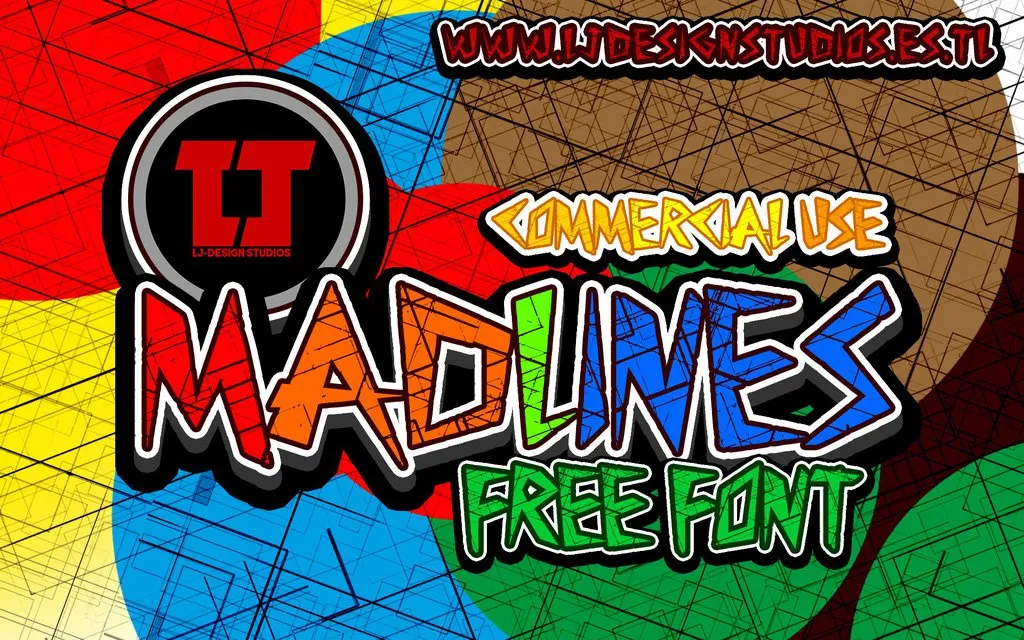
MadLines é uma fonte de graffiti criada pelo designer Hamilton. Ideal para quem busca estilo vibrante e ousado no seu design, esta fonte traz a essência do grafite urbano com liberdade e personalidade. Suas formas livres e coloridas são perfeitas para criações que desejam expressar-se de maneira única e autêntica. Se você aprecia e gosta desta fonte, consideramos importante reconhecer o esforço do designer Hamilton ao criar um trabalho tão original. Para apoiá-lo na sua jornada criativa, oferecemos a possibilidade de fazer uma pequena doação para que possa continuar desenvolvendo novas fontes incríveis como esta. Gostaríamos muito de saber da sua opinião e da forma como usa MadLines em seus projetos.